Retour sur un stage de 2 jours à Lyon, hébergé par l’association Les Chemins de l’Ecriture et animé par le grand calligraphe italien Massimo Pollelo. Nous avons travaillé la gestuelle en se basant sur la Chancelière et en utilisant différents outils (j’ai encore mal aux dents, rapport aux vibrations du cola-pen, mais cette exploration était très enrichissante !).
La plume Speedball
Une des révélation du stage fut sans doute l’utilisation des plumes larges Speedball pour tracer la gestuelle.
La Speedball est une plume américaine biseautée d’une grande souplesse, contrairement à sa cousine allemande la Brause qui est très dure. Elle dispose d’un réservoir en laiton, et existe en 6 tailles.
Je l’avais déjà utilisée pour la Chancelière formelle, car elle permet d’ajouter une bonne dynamique aux lettres grâce à sa souplesse. Comme elle glisse très bien sur le papier, il était en effet opportun de l’utiliser pour la gestuelle.
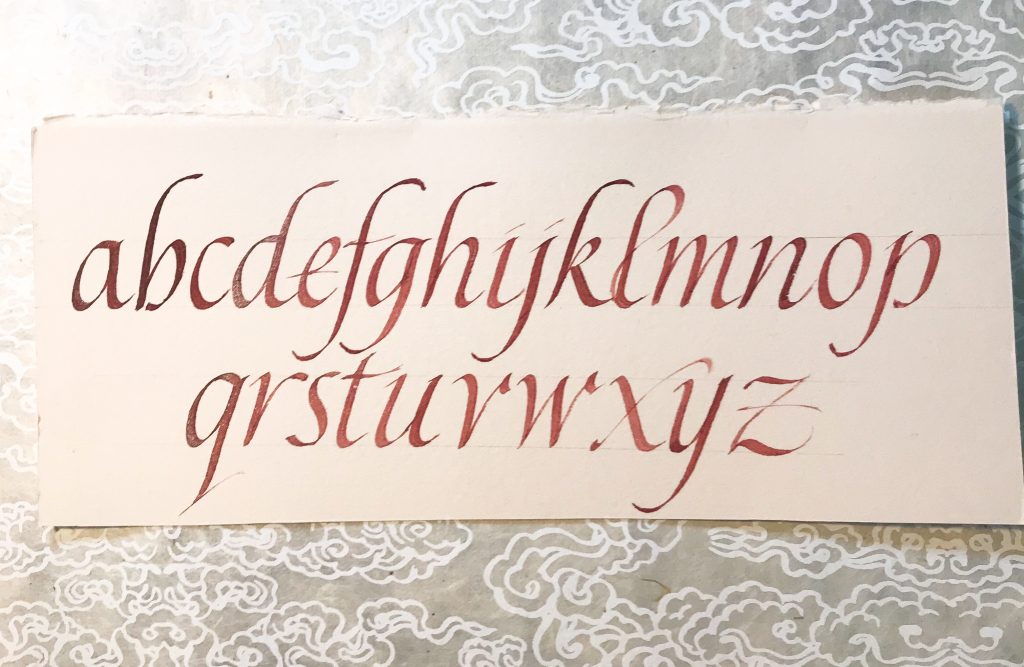
J’avais déjà essayé toute seule dans mon coin de faire de la gestuelle avec une plume large, sans grand résultat. Les explications et démonstrations de Massimo, ainsi que son approche, m’ont permis d’apprivoiser un peu mieux l’outil.
On commence par travailler le trait, comme toujours, en veillant à être bien tendu (mais pas raide). Le geste est énergique, et on hésite pas à appuyer sur la plume pour bien marquer le contraste dans les traits descendants.
Pour la gestuelle, il faut beaucoup de liquide : donc de l’encre bien fluide, du brou de noix ou de la peinture (gouache ou aquarelle) bien diluée. La plume est trempée directement dans le pot, et non chargée au pinceau, et on y va.
Répéter le geste, travailler le rythme et le contraste
Il faut faire quelques lignes pour bien trouver sa position. En l’occurrence, j’ai un peu incliné ma feuille pour être plus à l’aise. Il faut aussi, bien sûr, que le bras qui écrit puisse se mouvoir sans contrainte : donc on veille à travailler sur un plan bien dégagé.
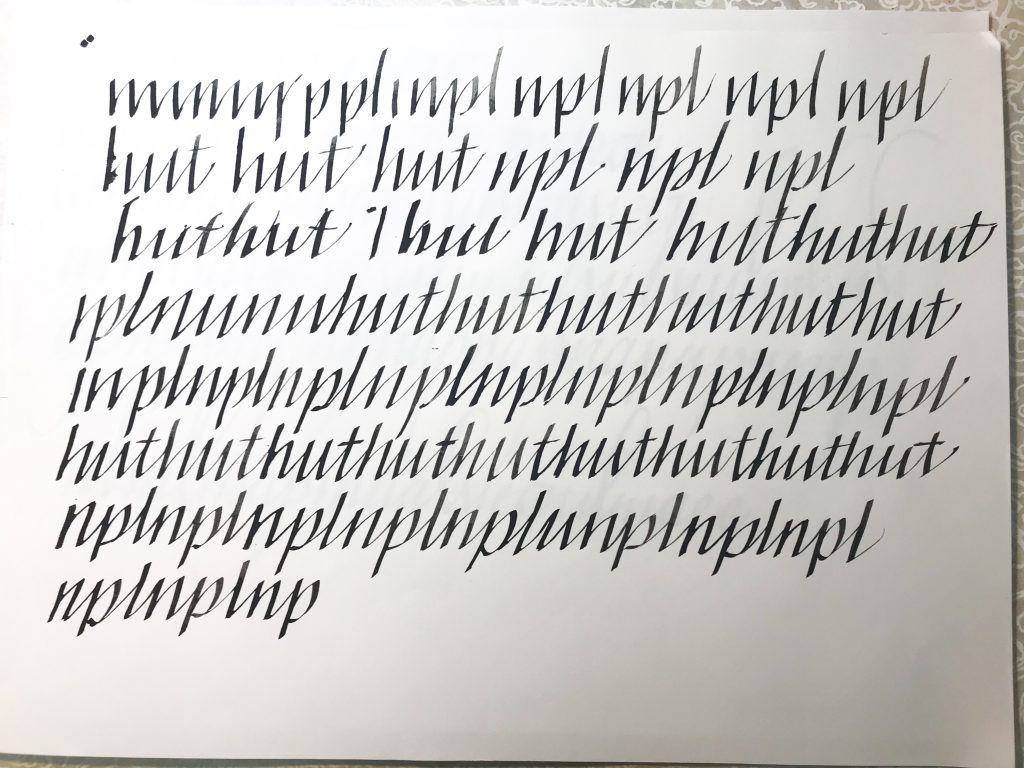
Nous avons ensuite travaillé les lettres ascendantes et descendantes, en exagérant parfois les hauteurs pour donner du rythme et du contraste. Nous avons aussi travaillé serré, puis un peu plus espacé. Le plus difficile est de veiller à la régularité.
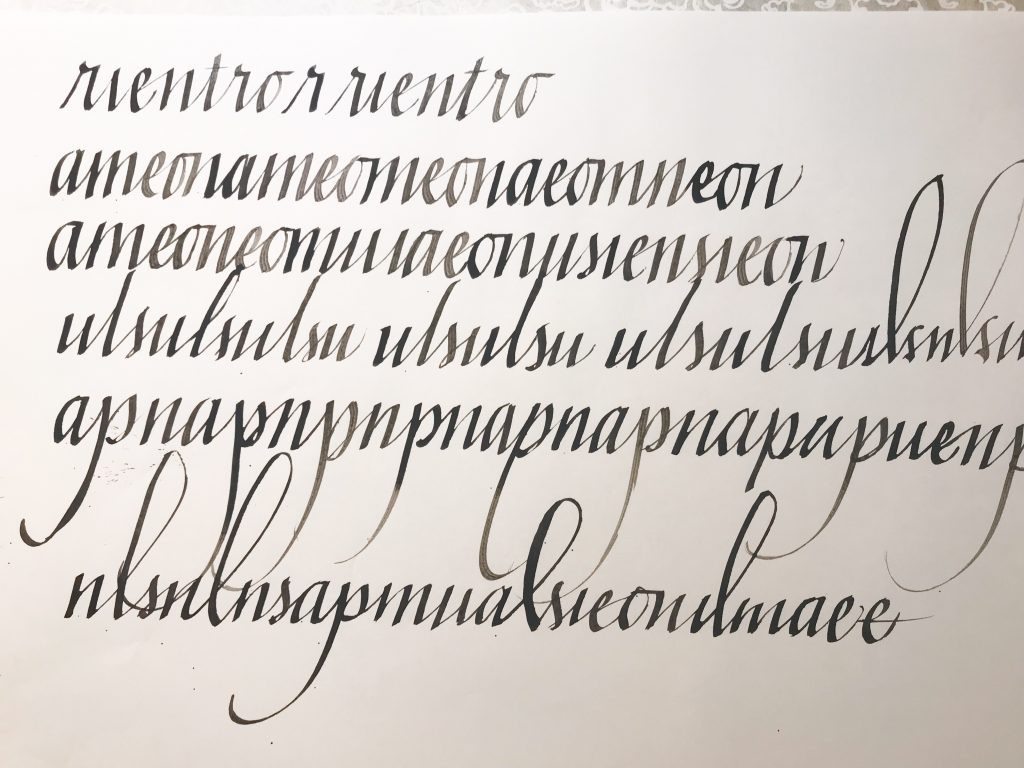
Pour bien imprimer le geste, Massimo nous a recommandé de travailler sur des séquences de lettres intéressantes, et de répéter plusieurs fois cette séquence. De la répétition vient l’habitude, notre psycho-motricité est mobilisée, tous les sens sont en éveil y compris l’ouïe avec le crrr..crrr..crrr… cadencé des plumes des stagiaires. Nous avons ensuite choisi un mot avec des lettres ascendantes et descendantes, et l’avons répété encore et encore en jouant sur des variations en hauteur ou en largeur. J’ai dû écrire à peu près 200 fois le mot « misanthrope », et en effet, à force de répétition, ça rentre et on crée des automatismes.
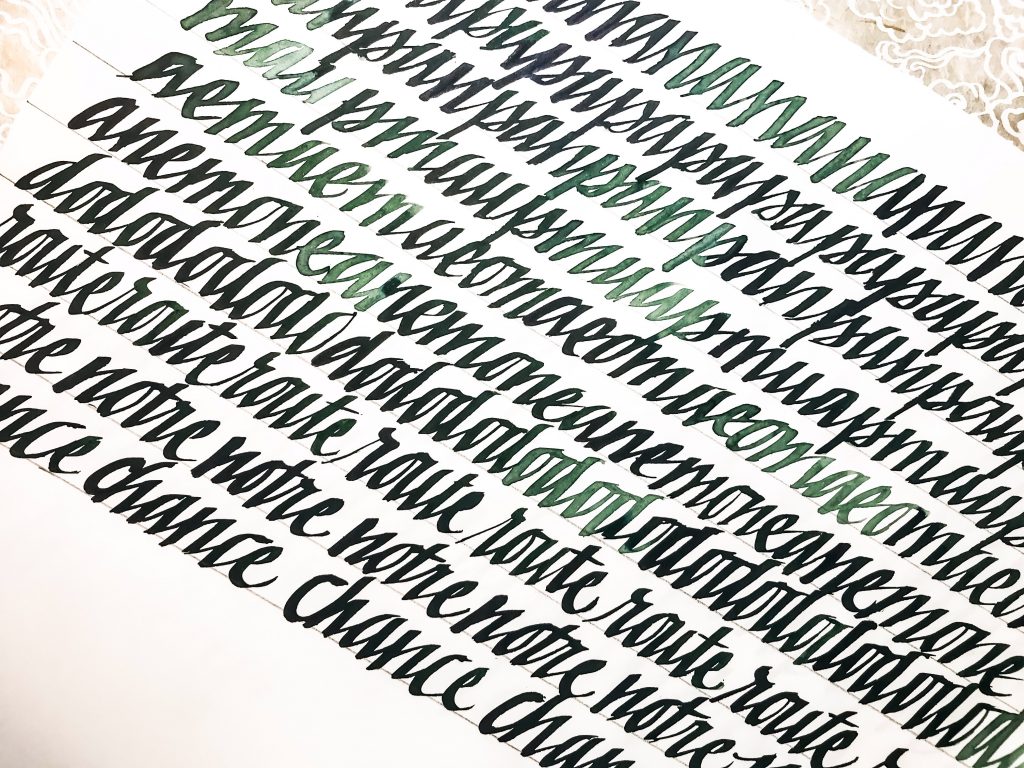
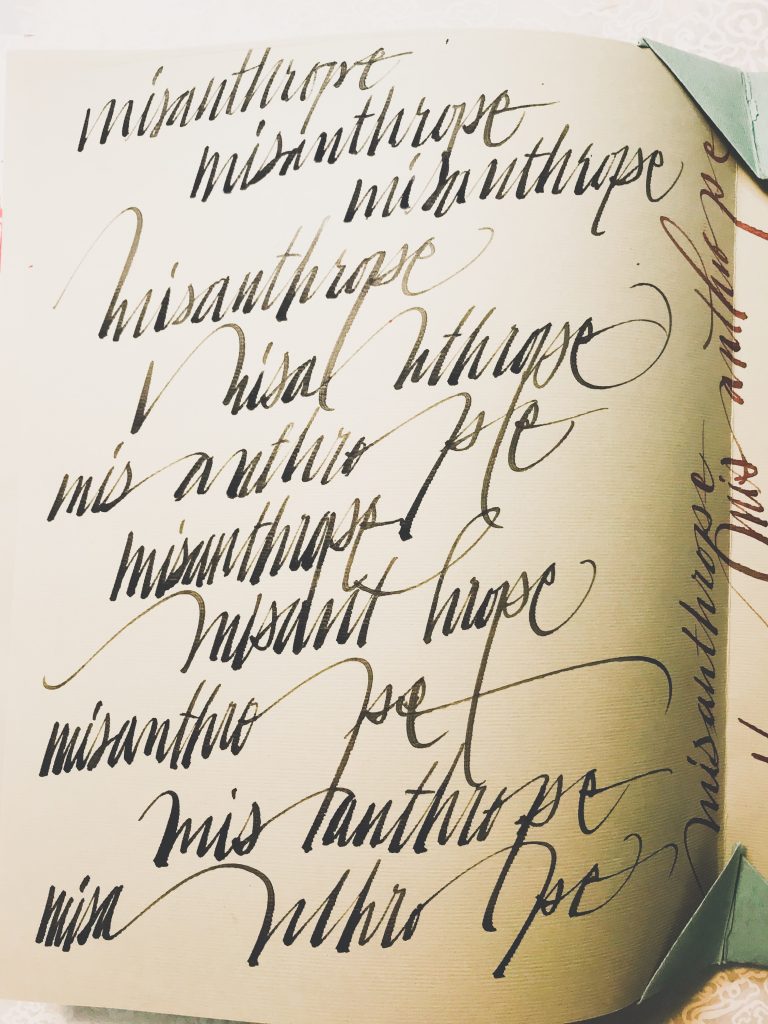
Travailler sur de beaux papiers
Après quelques exercices sur du papier ordinaire, Massimo nous a demandé de continuer nos exercices sur du beau papier. Ça fait un peu mal de s’exercer sur du beau papier, n’est-ce pas, mais cette approche est vertueuse dans le sens où la plume glisse mieux et l’encre a un rendu beaucoup plus beau que sur du papier ordinaire.
On hésite toujours à se lancer avec du beau papier parce qu’on a peur de rater, ou parce qu’on souhaite le garder spécialement pour des travaux très réfléchis, des chefs d’œuvre (!). Mais c’est une erreur : on apprend énormément en utilisant du papier de qualité, et des papiers de qualité différentes. Ce travail n’est pas perdu, on peut toujours en faire quelque chose de sympa : pour des enveloppes, des cartes, des collages, etc. Lors du stage, l’idée de Massimo était de nous faire réaliser un livret en origami, une très belle idée pour rassembler tous ces travaux dans un book d’artiste.
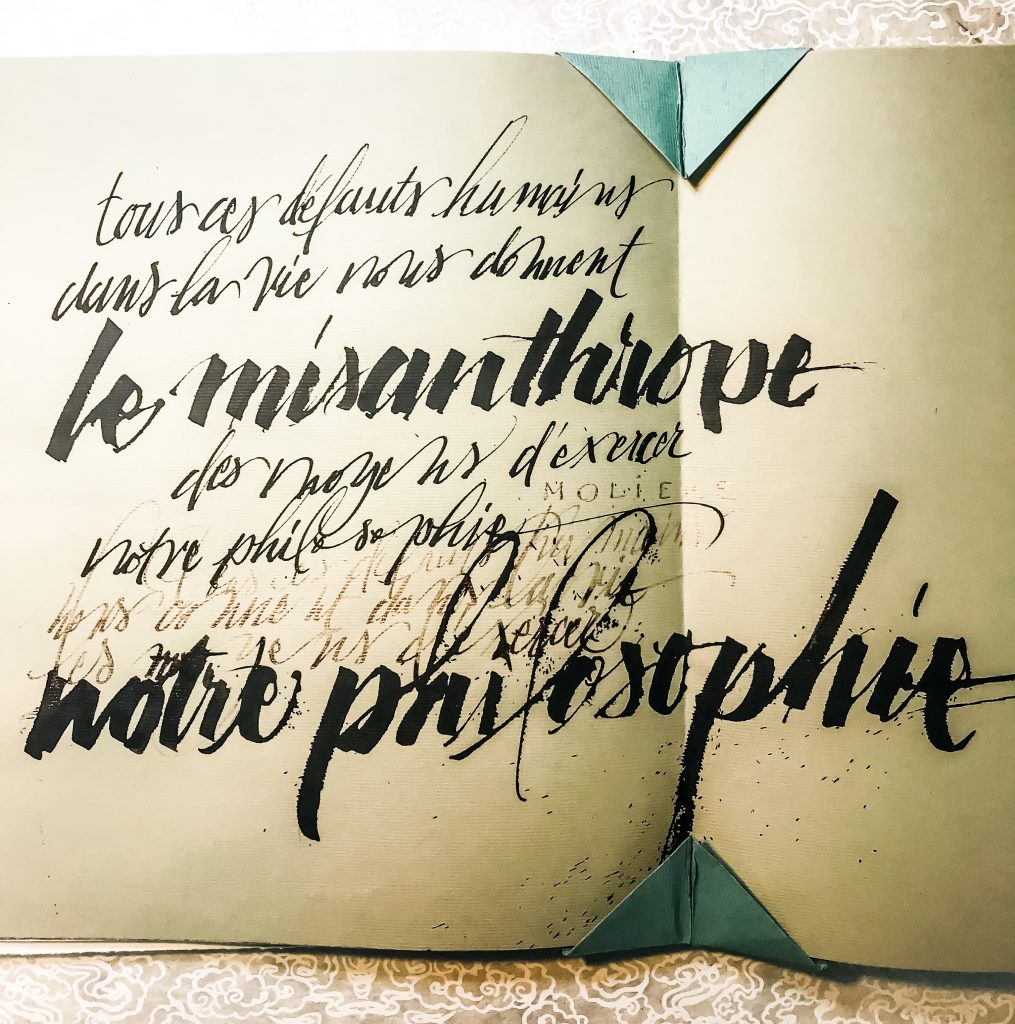
Pour le stage j’ai travaillé sur du papier Rosaspina de Fabriano (autant prendre du papier italien !), du Ingres MBM et du papier Ingres de couleur. Si vous cherchez de beaux papier pour calligraphier en gestuelle, n’hésitez pas à vous tourner vers les papiers « Edition d’Art’. Ils sont faits pour l’impression (lino, estampe), donc l’encre ne fuse pas dessus, la trace est précise.
Il reste encore du travail, de la répétition, pour peaufiner le style et obtenir un équilibre bien contrasté. Ce stage était vraiment très chouette, avec en sus la compagnie haute en couleur de mes amies calligraphes Agathe Richard, Marine PSM, Claudine Brunon, Céline Foissey, mon amie Roseline, Hélène de Papier Mirabelle, Christine de Quintessence_aquarelletters, Jean Mi aka @layote, et les élèves de l’asso.
Pour aller plus loin, je vous invite à découvrir la très belle vidéo de Claudine, mettant en scène son travail durant le stage au travers du carnet origami.